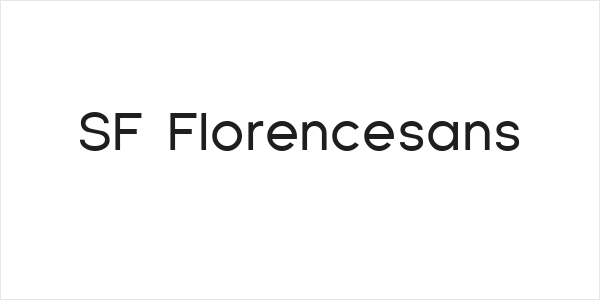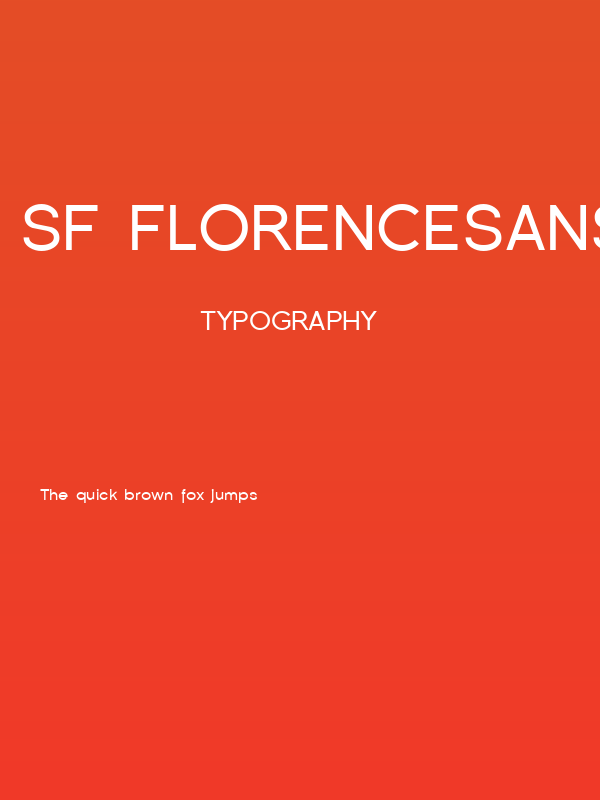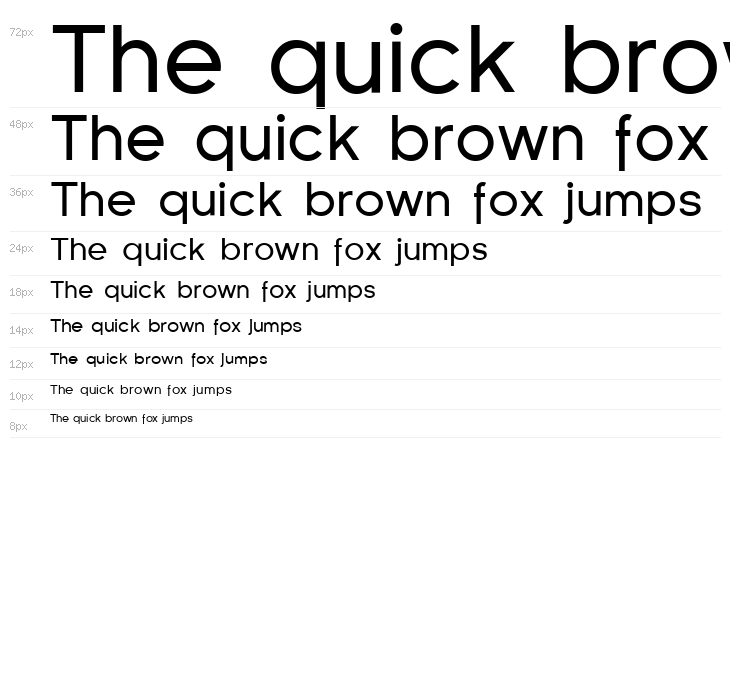
SF Florencesans Font
✎ Sans Serif
| 使用场景 | Headlines, Body text, Logos |
| 推荐项目 | Ideal for branding, web design, advertising, and editorial projects where a modern and clean aesthetic is desired. |